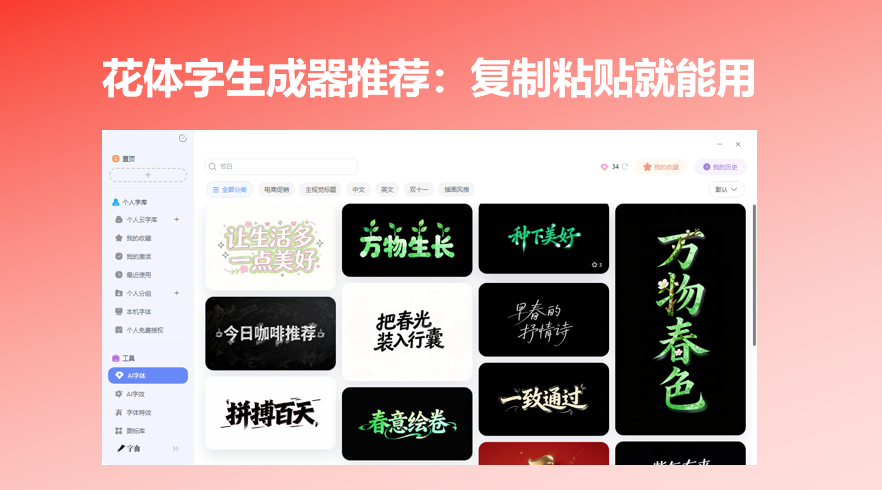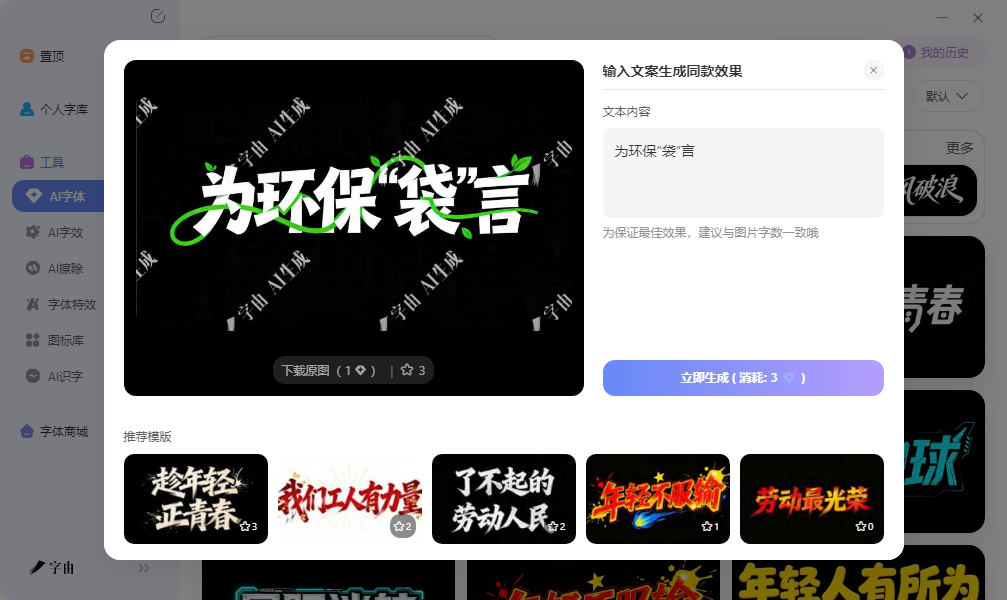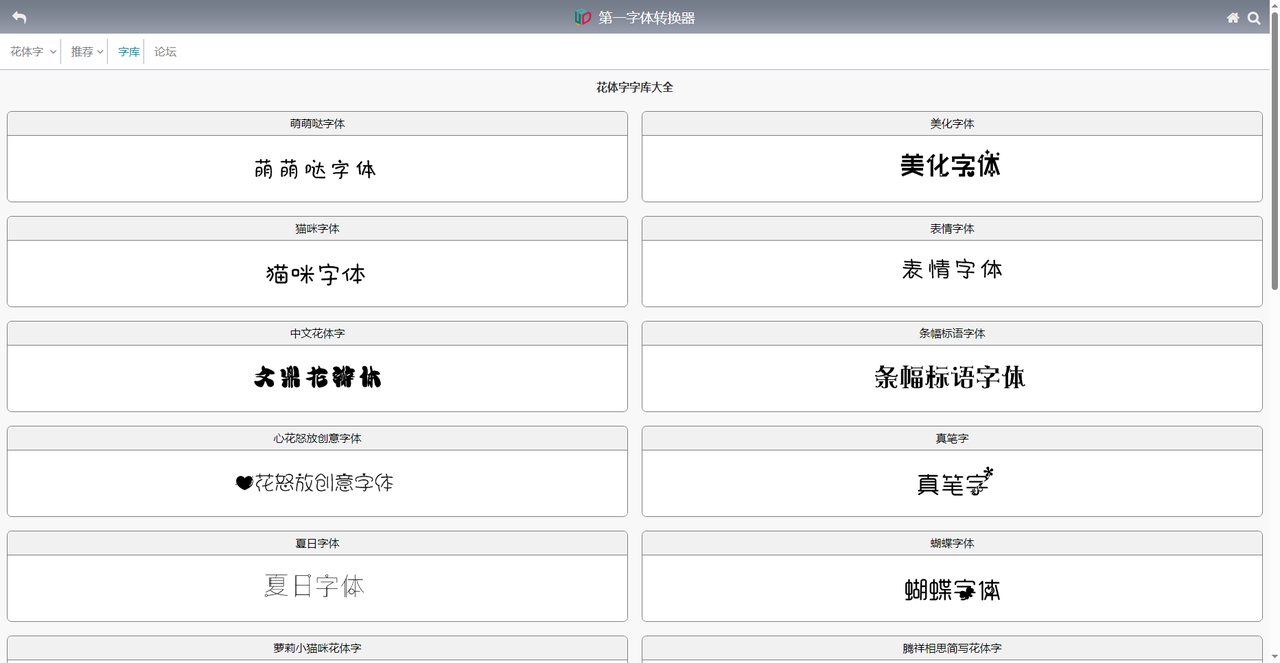
花体字生成器推荐:复制粘贴就能用
今天要推荐的主要内容是在线花体字生成器:输入文字,自动转换成花体、粗体、哥特体、气泡体,一键复制,粘贴到任何地方都能正常显示。原理是Unicode字符映射——把普通字母替换成特殊符号区域的花体字符,所有设备和平台都支持,不依赖对方有没有装字体。今天选了5款实测好用的花体字工具,需要的可以直接收藏。
先看字由:后面要介绍的工具生成的Unicode花体字是纯文本,适合发朋友圈、改昵称。但如果你需要把花体字用在海报、封面、名片上,纯文本不够——你想要的可能是带背景、带装饰、带纹理的精致花体字效果。
字由的AI字体功能里有花体、手写、装饰风格的模板。打开字由客户端或网页版,在“AI工具”下找到“AI字体”,然后在搜索框输入“花体”“手写”“装饰”“calligraphy”等关键词,或者直接浏览“手写体”分类。你会看到很多不同风格的花体模板——有的每个字母都带藤蔓装饰,有的像中世纪手抄本的哥特体,有的像用羽毛笔写出来的草书。
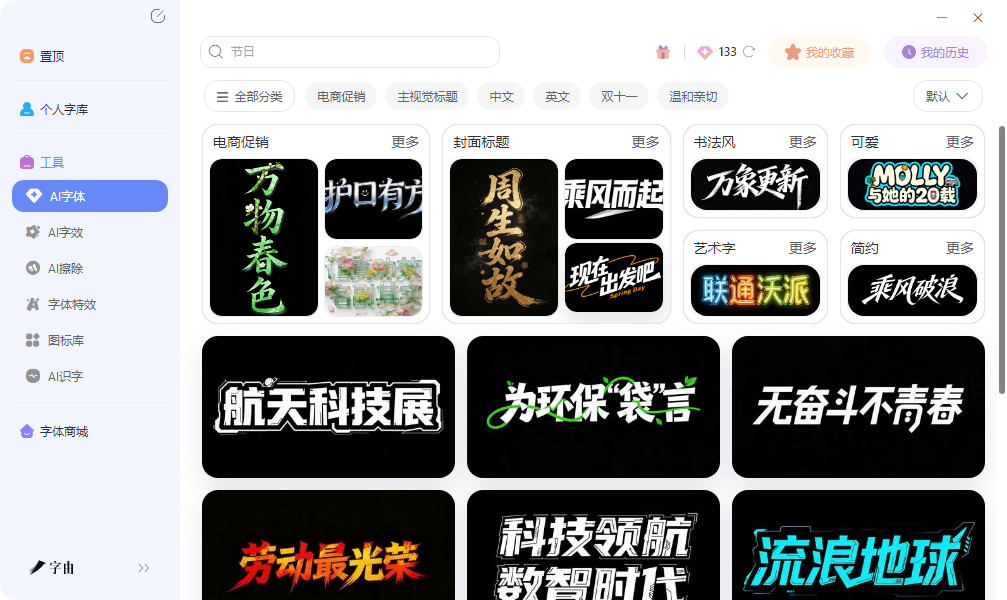
具体步骤如下:
第一步:选中一个模板,点击“做同款”。第二步:在右侧输入框里,把模板里的示例文字换成你自己的文案。注意一个细节:最好和模板原来展示的单词长度相近。比如模板是“Love”,你换成“Hope”可以;如果换成“Beautiful”,字母数多了很多,排版可能不够紧凑。第三步:点击“立即生成”,等待20到30秒,系统就会输出一张高清花体字图片。默认背景透明,下载PNG格式后可以直接拖进PS、Canva、剪映甚至PPT里。
2、第一字体转换器
第二个网站比较特别,它叫第一字体转换器。大多数花体字生成器只支持英文,因为Unicode花体符号主要覆盖拉丁字母。但如果你需要中文花体字怎么办?第一字体转换器专门做了一个“花体字字库大全”板块。打开页面,你能看到“萌萌哒字体”“猫咪字体”“表情字体”“中文花体字”“萝莉小猫咪花体字”“心花怒放创意字体”“夏日字体”“蝴蝶字体”等分类。这些不是Unicode转换,而是预先生成好的字体样式图片——每个汉字都被设计成特定的艺术字形。例如“萝莉小猫咪花体字”,每个汉字旁边都加了猫耳朵和猫爪装饰,非常可爱。输入文字后,选择你喜欢的分类,点击生成,就可以下载图片。
3、Refont
第三个工具是Refont。它的界面非常干净,没有广告,没有冗余的功能模块。打开页面,顶部是一个大型输入框,输入文字。下方立刻显示不同样式的转换结果。每行就是一款花式字体,花体、粗体、草书、哥特体、气泡体等等都有。样式数量不多不少,大约二三十种,但每种风格的区分度很高。不会像某些工具生成几百种几乎一样的样式。点击样式右侧的“复制”按钮,就能把转换后的文本复制到剪贴板,粘贴到目标应用。
实时性极佳——输入文字的同时,所有样式立刻刷新,完全不需要点击生成。适合反复修改文字的场景,比如你还在犹豫用哪个名字、哪句slogan,可以直接在输入框里改,同时看到所有样式的效果。另外,Refont也提供了Logo生成器、海报制作等附加工具,但这些不是重点。核心功能就是快速多次生成和复制花体字。
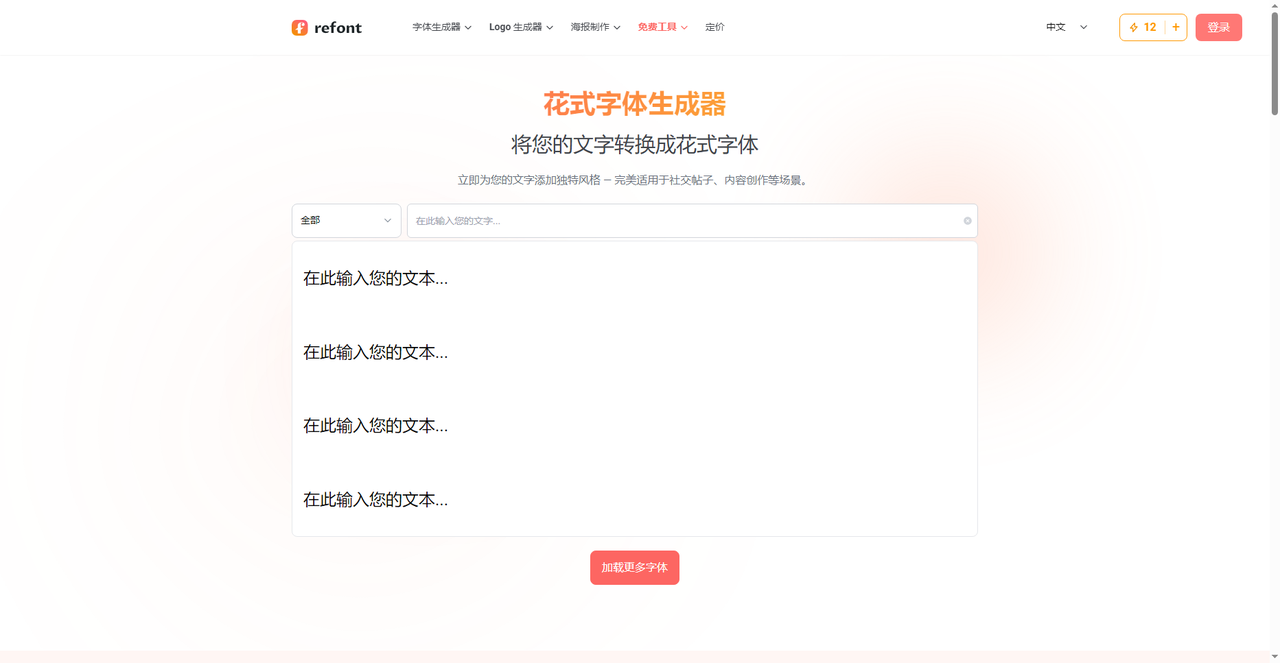
4、Fonttiner
第四个网站是Fonttiner。它不只是简单罗列样式,还提供了丰富的解释说明。输入文字后,下面会生成多种花体样式:Fraktur / Old English(哥特体/古英语)、Double Struck(双线体,常用于数学符号)、Serif Bold(粗衬线体)、Script Royal Bold(皇家草书)等等。每种样式右侧都有“复制”按钮。它专门用了一段文字解释这些花体字的技术原理:
“字体通过使用不同的Unicode字符生成不同的样式来工作。因此,您实际上并没有生成字体,而是正在获取花哨的Unicode符号,这些符号是为字母表、数字和其他每个小字母和资本出借者准备的。每个样式都是一组字符对,例如圆形或花哨的气泡字体字符映射。”
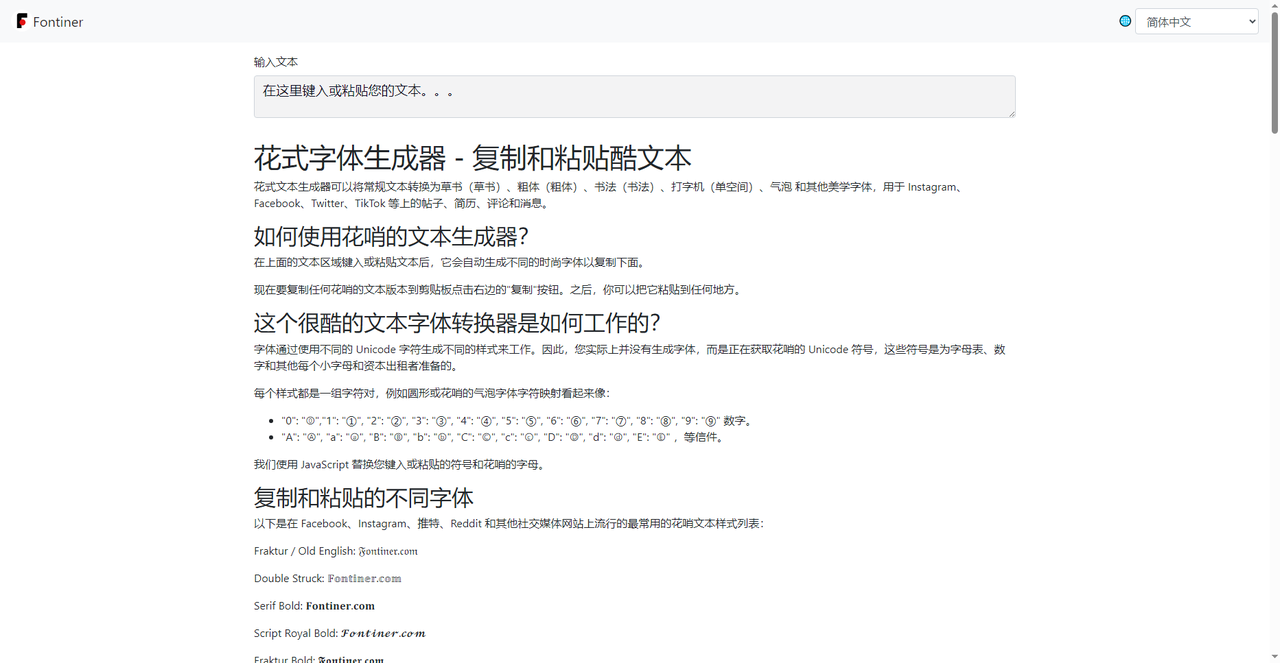
5、FontGenerator
第五个工具是FontGenerator。它的界面极简,只有一个核心功能:输入文字,下面的样式列表会自动更新。样式数量适中,包括花体、草书、哥特体等。页面右上角有复选按钮方便快速复制。没有多余的广告、社交分享按钮或复杂设置。做技术文档的代码注释需要花体字、发GitHub README时需要特殊效果、偶尔改一次游戏ID的用户。它不会记录你的任何信息,也无需注册。加载速度快,没有任何多余内容。相比前几个工具,它的样式确实不够华丽,但胜在稳定。因为是纯前端实现,编辑体验流畅。
相比于字由要生成图片,FontGenerator纯文本;相比于第一字体转换器,它不支持中文花体;相比于Refont,它的样式数量少了一些。但如果你只是偶尔快速转换一个单词,它是最干净的解决方案。
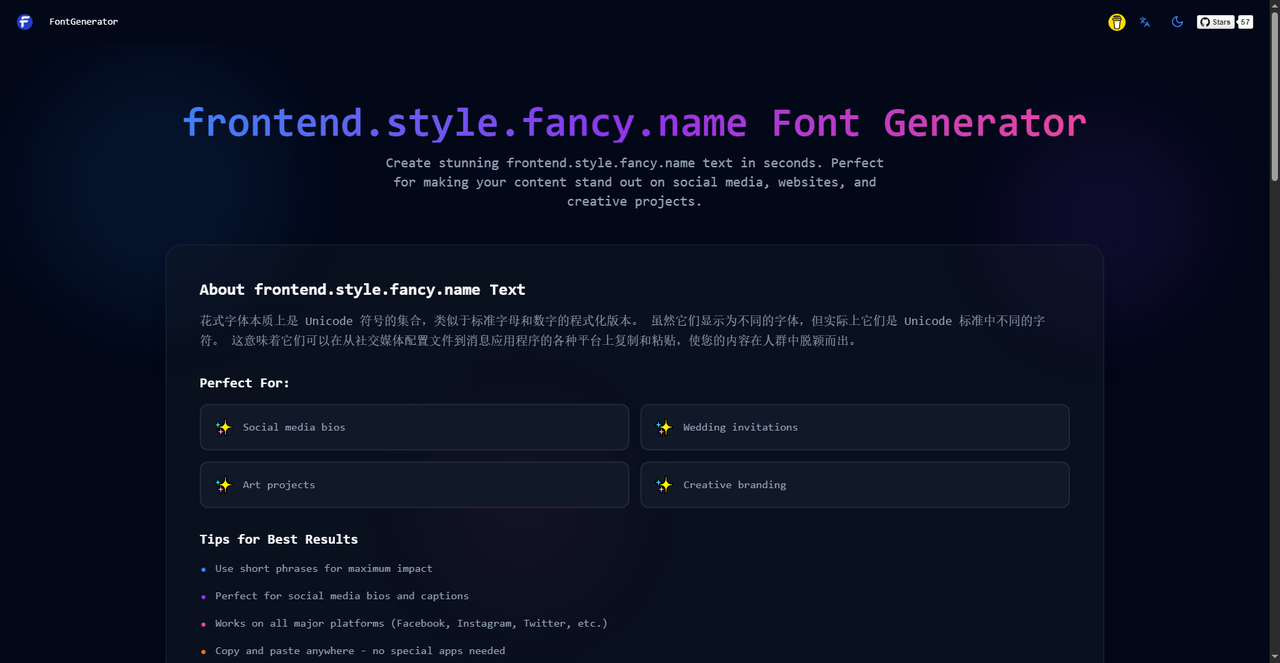
以上介绍的工具里,字由生成的是花体字图片,适合做海报标题和品牌水印,效果更精致,而且基本上是免费的;第一字体转换器有丰富的中文花体字库和可爱主题,适合做头像签名;Refont界面清爽,样式识别度高,适合普通社交分享;Fonttiner样式丰富,附带原理说明,适合想了解技术细节的用户;FontGenerator最简单直接,适合偶尔用一次的轻度用户。如果要问到底选哪个,那就是看你是发朋友圈、做头像还是做设计。输入文字,试一遍就知道。